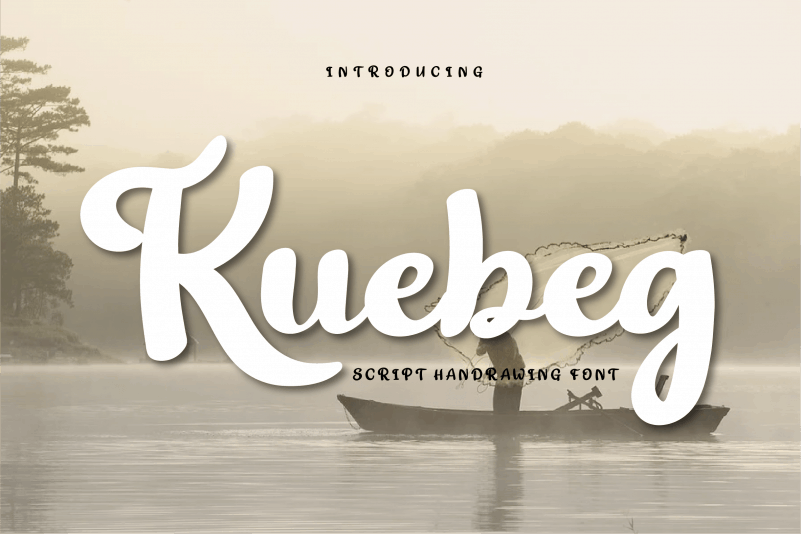
Kuebeg Script Font – Download Grátis
A Kuebeg Script Font é uma elegante fonte à base de escritura chinesa ideal para adicionar um toque único a projetos pessoais ou profissionais, especialmente em aplicativos digitais e websites. Se você está procurando por uma fonte que transmite sofisticação e autenticidade, esta seria sua escolha perfeita. O designer twinletter criou Kuebeg Script Font para fornecer um estilo de escritura chinesa fluido e atraente. A característica mais distintiva da Kuebeg Script Font é seu design suave e elegante que mantém fiel à natureza do estilismo chino, enquanto oferece um recurso profissional suficiente para atender aos projetos digitais modernos. Essa fonte é perfeita para criar texturas agradáveis em qualquer projeto visual ou tipográfico em que seja necessário adicionar uma nota de autenticidade e sofisticação à sua mensagem. Kuebeg Script Font está disponível gratuitamente para uso pessoal, mas se você gostar do design e quiser contribuir financeiramente para o desenvolvimento da fonte, os criadores oferecem a opção de doação através do PayPal. Este é um ato que respeita tanto o designer quanto aqueles que desejam usar esta fonte gratuitamente, valorizando assim a arte e o trabalho adotado neste projeto.